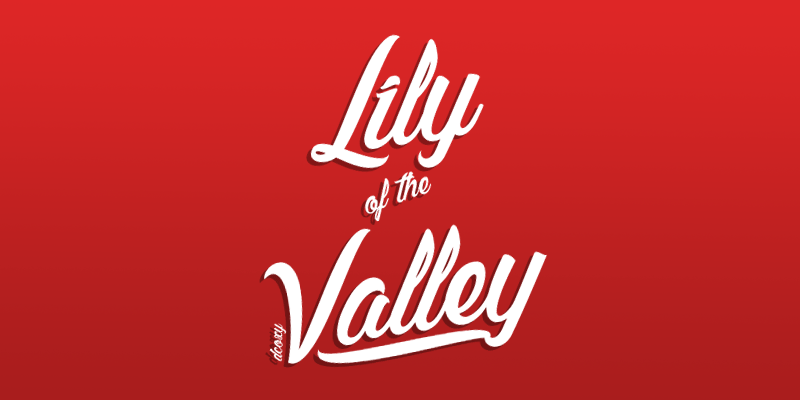
Lily of the Valley Font
A fonte ‘Lily of the Valley’ é uma delicada escolha para qualquer projeto que busque uma sensação floral e leve. Com sua tipografia script, esta font oferece um toque encantador que complementa perfeitamente projetos de marca pessoal, cartões de aniversário ou até mesmo em artigos educacionais e acadêmicos. Ela tem três versões: uma regular, outra alternativa com linhas mais suaves e ainda uma opção mais leve que mantém seu charme sem se tornar excessivamente frágil. Esta font é perfeita para quem valoriza um design cuidadoso e elegante. Ao adquirir a licença da fonte ‘Lily of the Valley’, você terá acesso a todas essas versões, garantindo que sua identidade gráfica seja sempre única e convidativa, independentemente do projeto em que for utilizada.